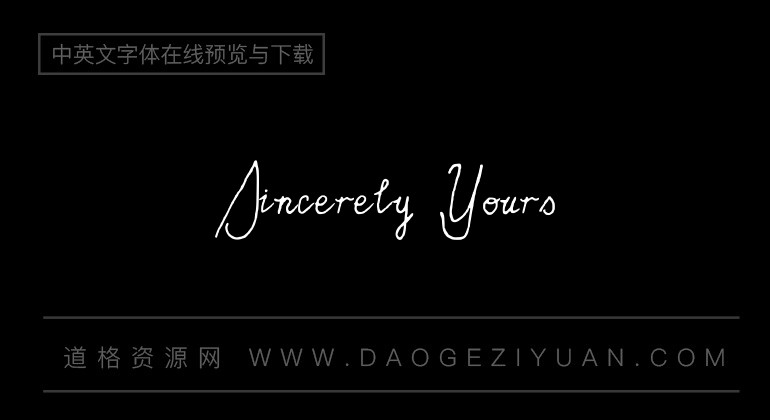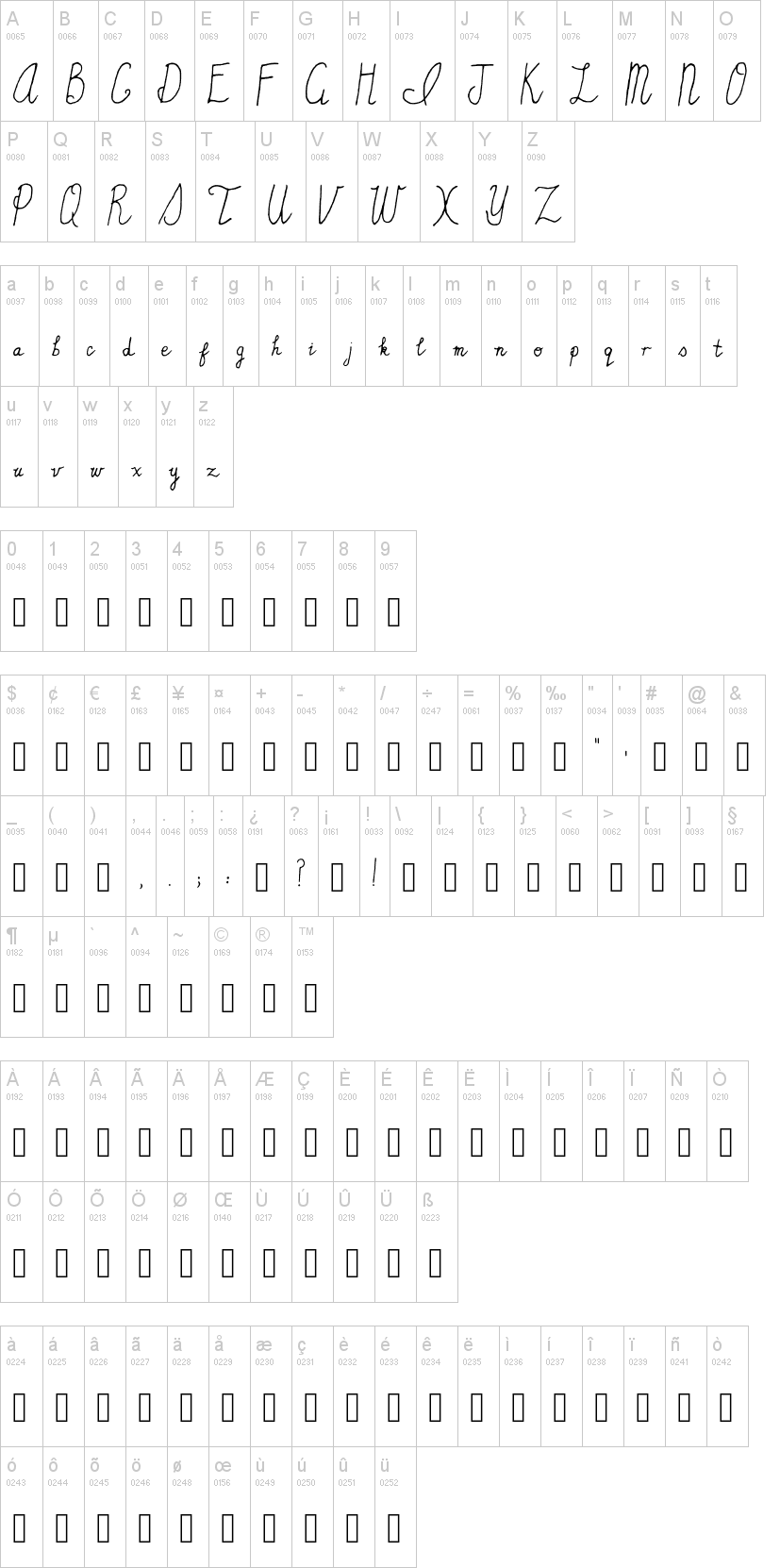
? Sincerely Yours 是一款非常流行的英文字体,它的特点是文字的笔画比较细腻,给人一种优雅、精致的感觉。它的字体比较细,但是也有一些粗体,有助于强调重点。它适合用于宣传单,海报,网页,书籍,杂志等。内容介绍
Sincerely Yours是一款非常不错的手写艺术字体,具有很好的视觉感,适合于文化类的宣传设计、商业类品牌的广告和产品包装设计以及个性化文字排版等较多场景。